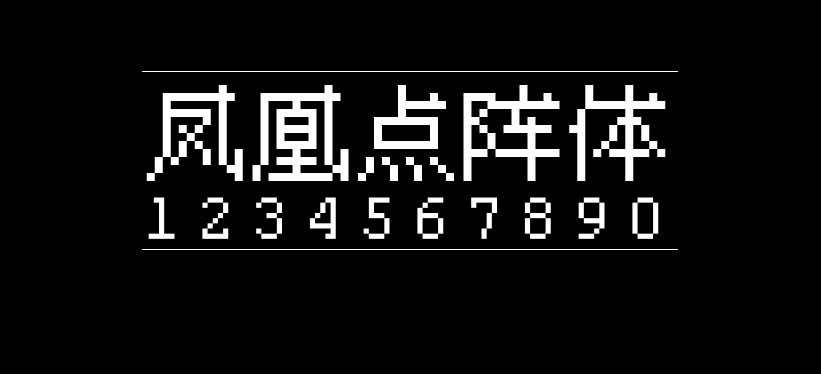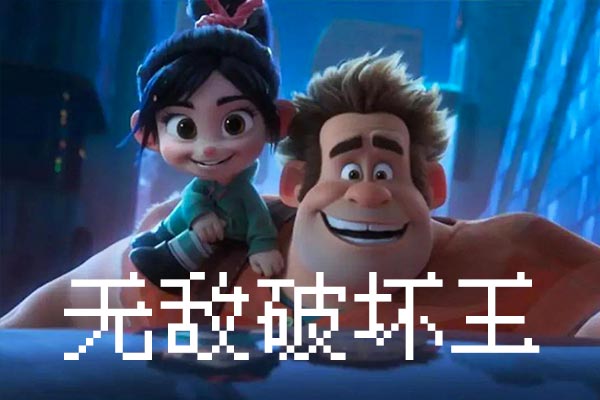
凤凰点阵体
凤凰点阵体(VonwaonBitmap)的作者是中国大陆的Haoyu Qiu,凤凰点阵体是免费的中文像素字体,使用 CC0 1.0 协议发布,属于公有领域。字模基于开源项目BitmapFont,针对汉字与非汉字、不同字号、字体之间的搭配使用进行了优化。
压缩包中有  12px 和 16px 两个版本的字体(对应 9pt 和 12pt),这是它们各自所使用的基准字模的像素高度。字号设置为对应尺寸的整数倍时,TTF 字体的显示效果最佳。
凤凰点阵体共包含 7543 个字符,其中汉字 6763 个。如果你非常在乎文件大小,可以使用 Lite 版,共包含 4041 个字符,其中汉字 3755 个(省略了较少使用的二级汉字)。Lite 版不包含日文假名、希腊字母、俄文字母、拼音、注音符号、制表字符、以及序号字符。如果您希望在你的项目中获得像素风格,例如像素风格的游戏和海报,这款凤凰点阵体就是个不错的选择。